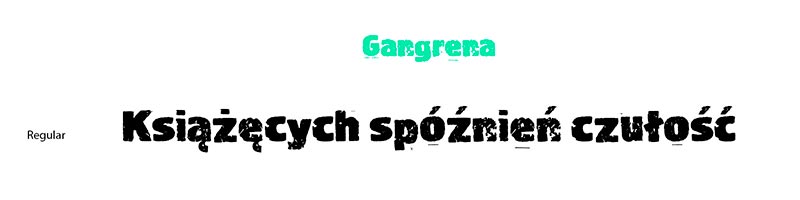
Font Gangrena
Rozszerzyliśmy zestaw używanych fontów o ozdobną Gangrenę, zaprojektowaną w 2016 roku przez Mateusza Machalskiego. Font posiada polskie ogonki.